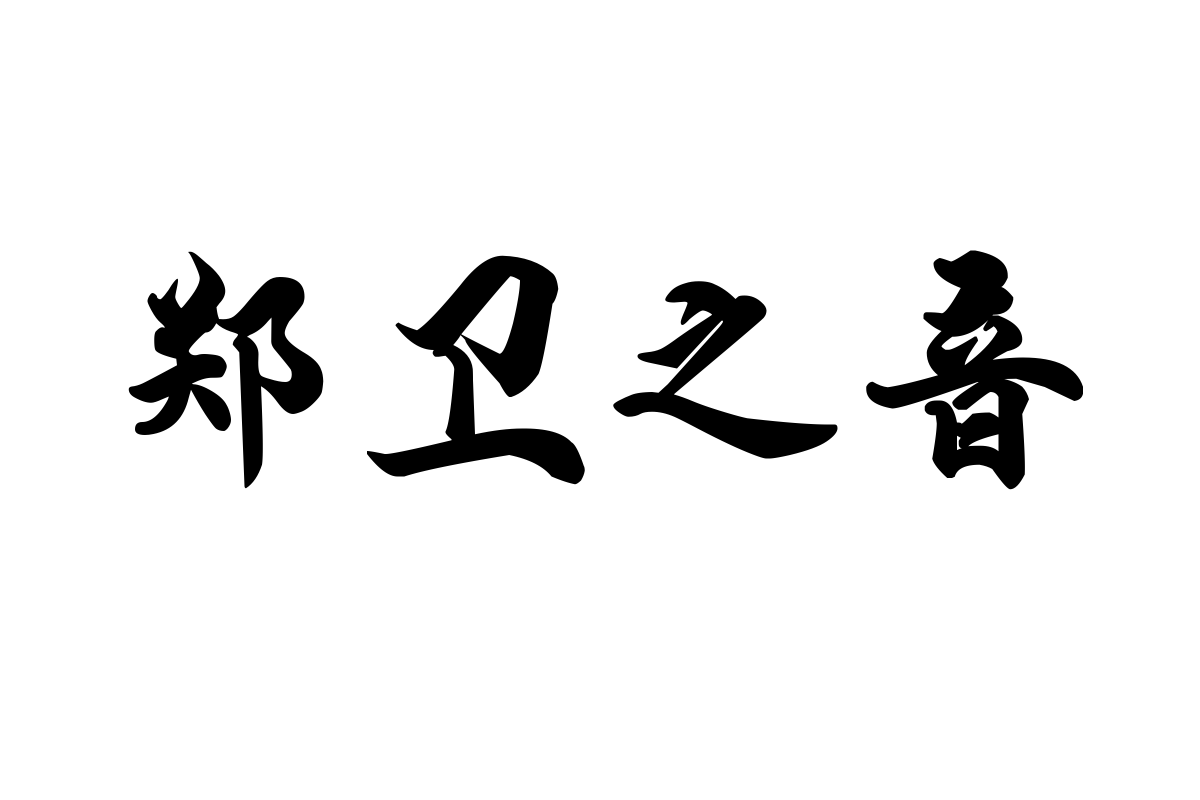
段宁毛笔行书字体是一种独特的书法风格,它结合了传统的行书和现代的毛笔书写技巧。这种字体的特点是笔画流畅、结构紧凑,既有传统的行书韵味,又不失现代感。
段宁毛笔行书字体的特点如下:
1. 笔画流畅:段宁毛笔行书字体的笔画流畅自然,没有过多的装饰性笔画,给人一种简洁而有力的美感。
2. 结构紧凑:这种字体的结构紧凑,每个字都紧密排列在一起,使得整个作品看起来更加整齐有序。
3. 传统与现代的结合:段宁毛笔行书字体既保留了传统的行书韵味,又融入了现代的毛笔书写技巧,使得作品既有古典之美,又不失现代感。
4. 个性化:每个书法家都有自己的独特风格,段宁的毛笔行书字体就是他个性化的表现,展现了他的艺术才华和个性魅力。
总的来说,段宁毛笔行书字体是一种融合了传统与现代、简约与复杂的书法风格,具有很高的艺术价值和文化内涵。